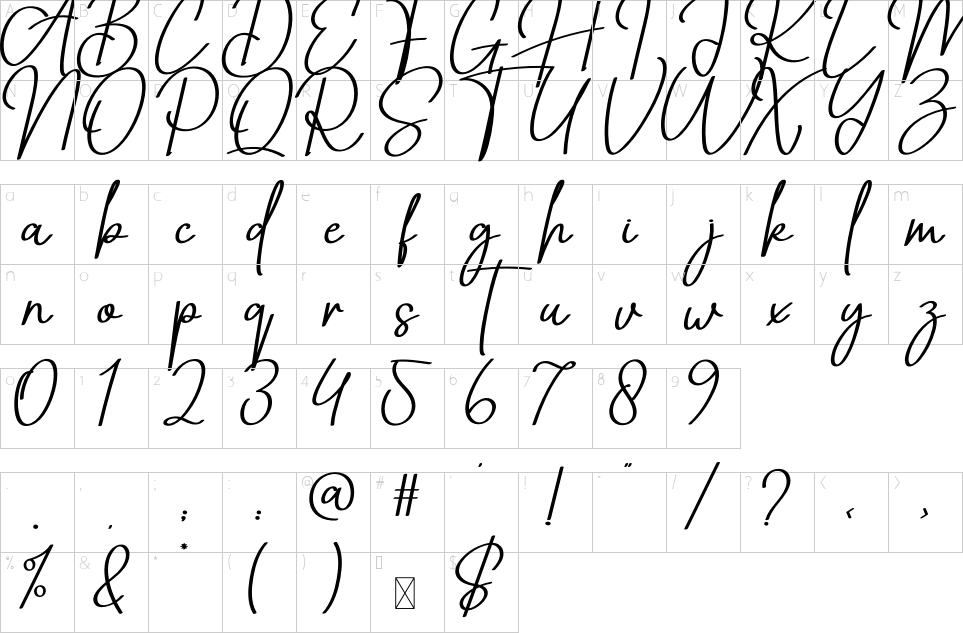
A fonte Margareta é um projeto de personalidade simples mas elegante, ideal para aplicativos de design gráfico que valorizam uma aparência confortável e acessível. Desenvolvida pelo designer scratchones, Margareta foi projetada para ser perfeitamente adaptada para uso em diferentes dispositivos, desde a versão para Windows até a versão para Mac. Como um font gratuito disponível para todos, é uma escolha versátil e versátil que não compromete o estilo, mantendo o equilíbrio perfeito entre simplicidade e elegância. Com mais de mil e quinhentas vezes baixada, Margareta é uma escolha segura para designers que buscam uma fonte gráfica de boa qualidade, sem ter que pagar por um license. Ideal para usar em qualquer projeto, seja para criar um design para a web ou para criar um layout de impressão, Margareta é uma fonte que merece uma oportunidade.